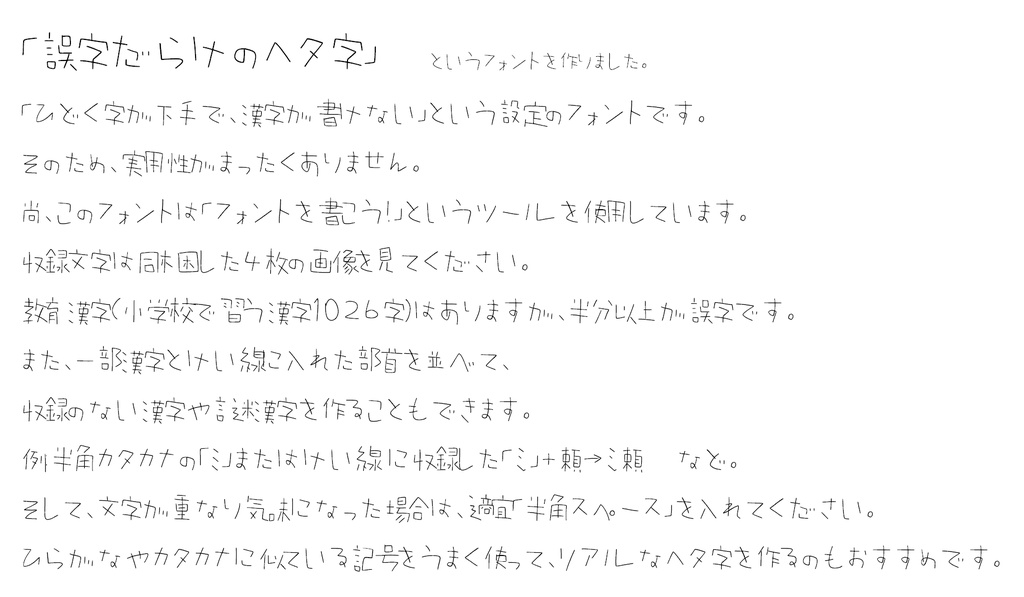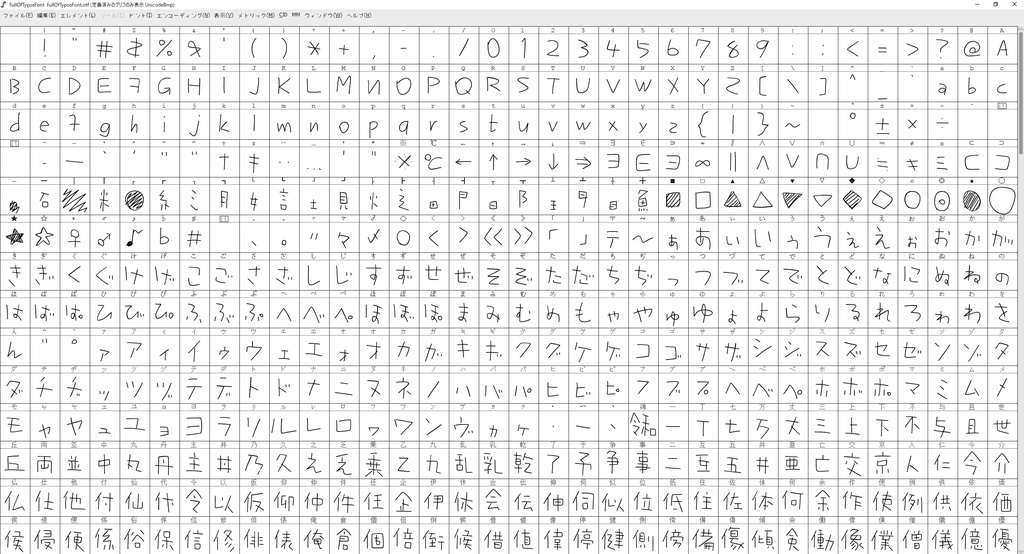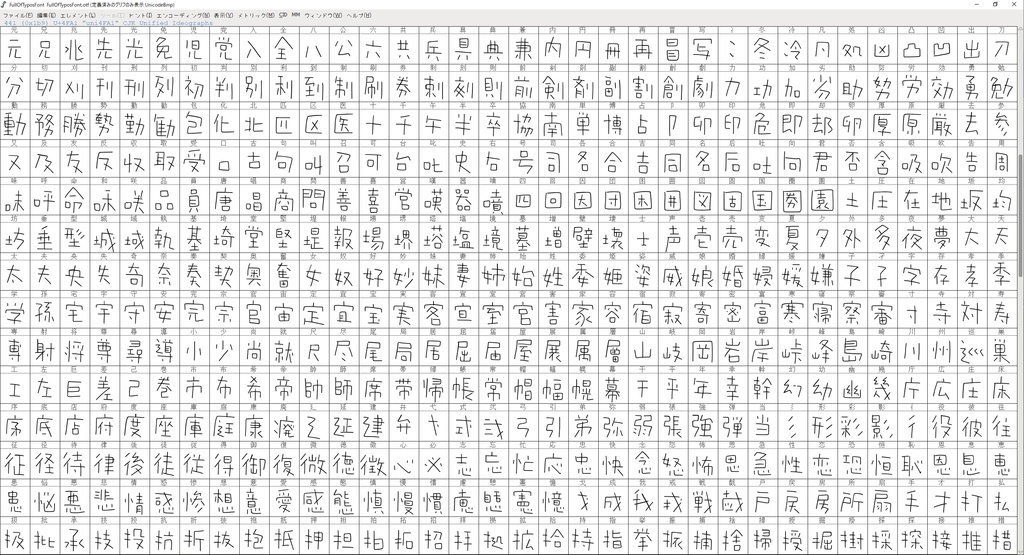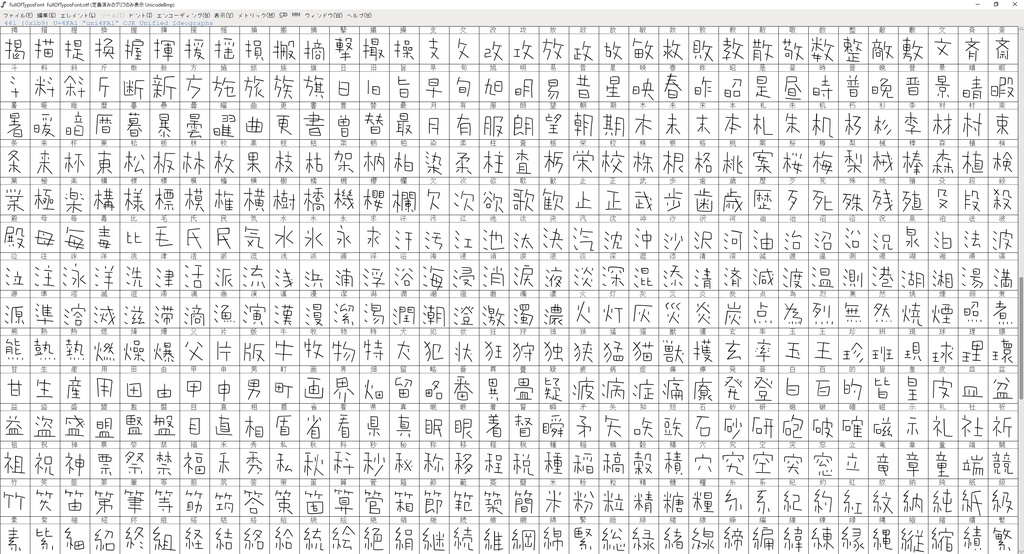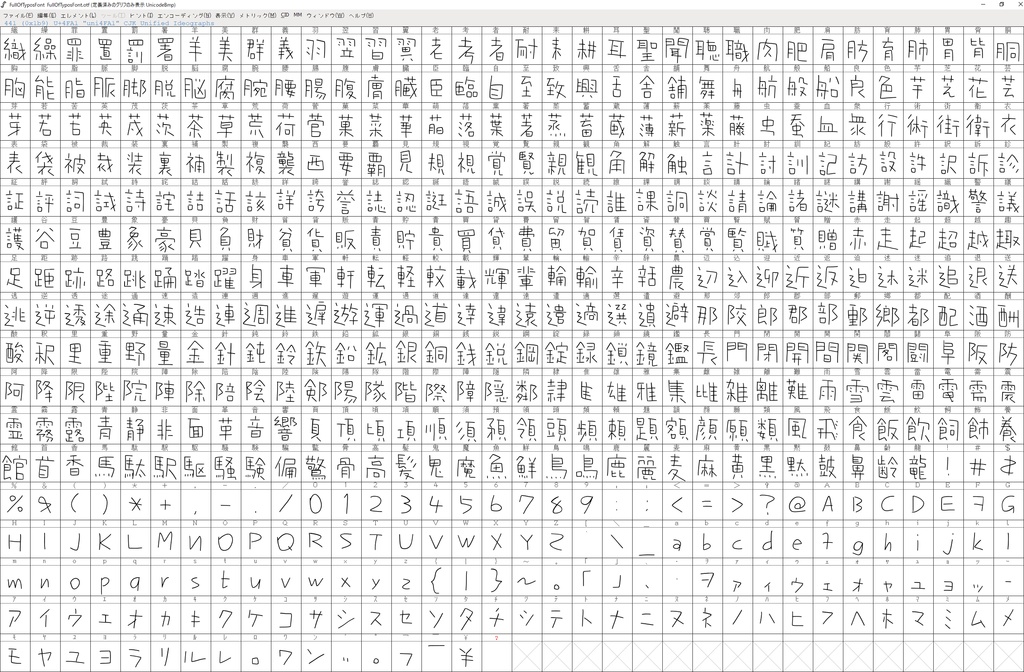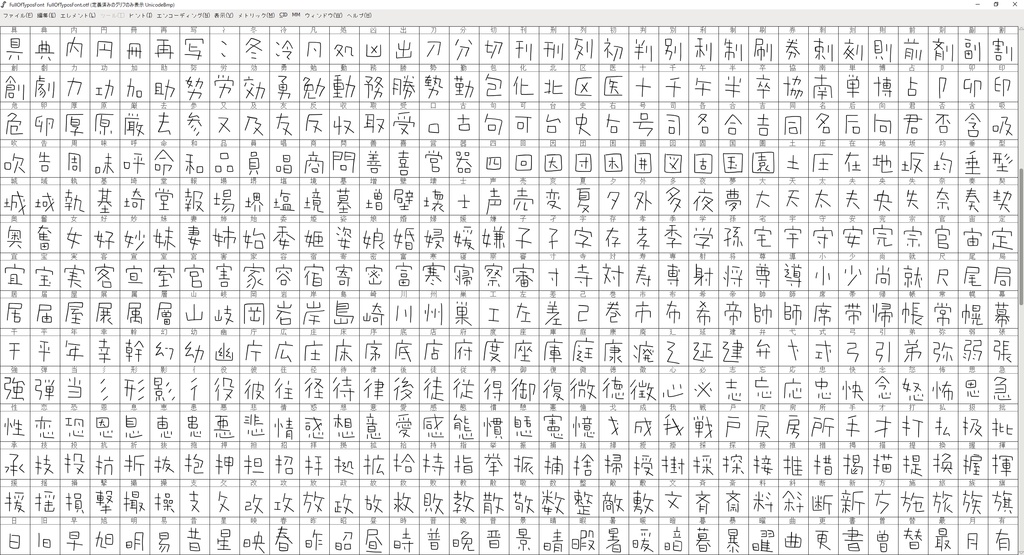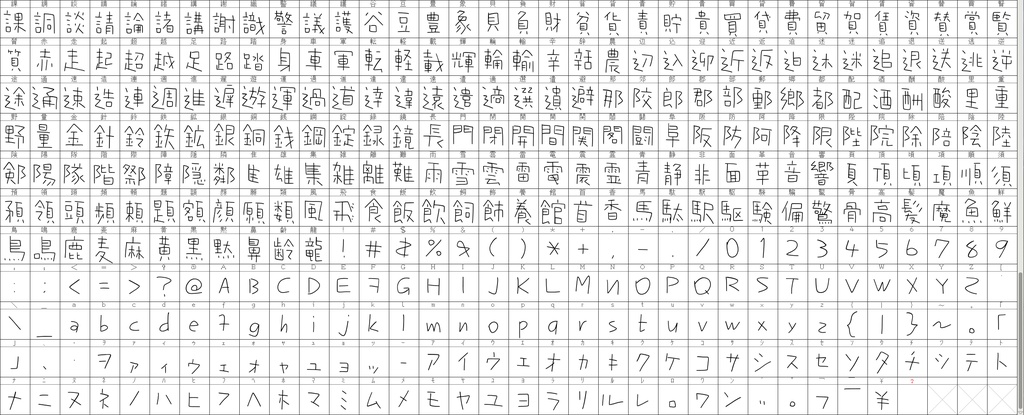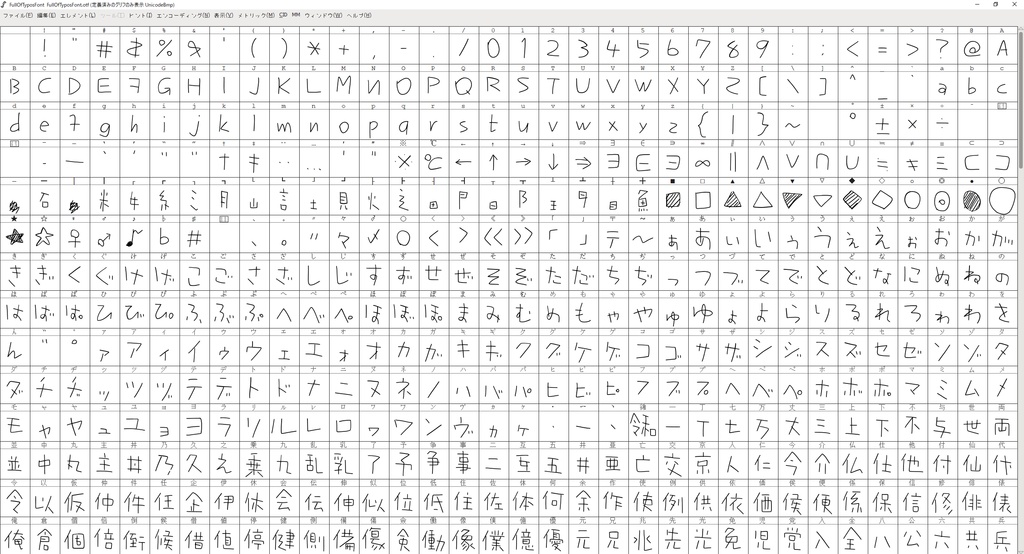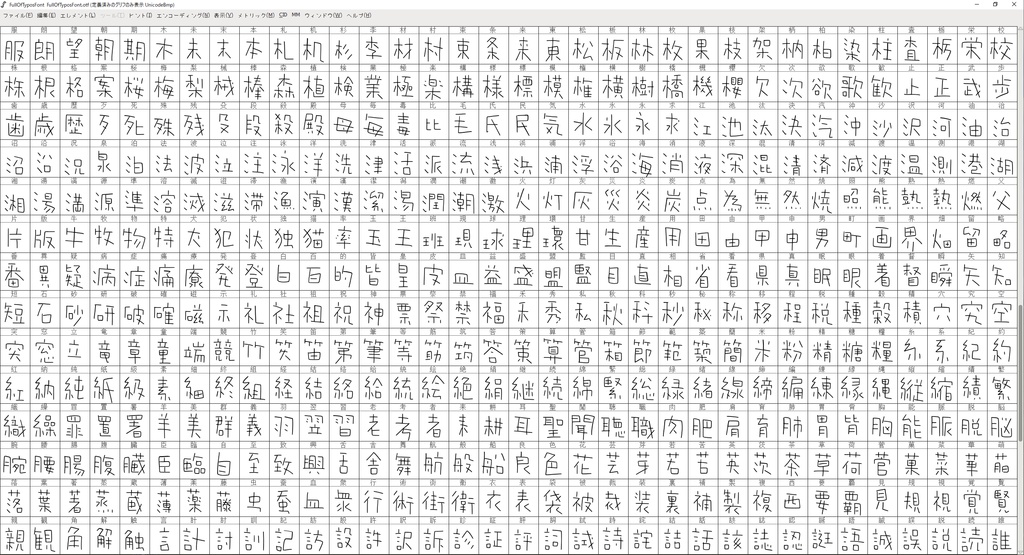
誤字だらけのヘタ字(フリーフォント)
「誤字だらけのヘタ字」というフォントを作りました。 「ひどく字が下手で、漢字が書けない」という設定のフォントです。 そのため、実用性がまったくないジョークフォントです。 尚、このフォントは「フォントを書こう!」というツールを使用しています。 https://buttaiwan.github.io/writemyfont/ja.html 収録文字は同梱した4枚の画像を見てください。 商用利用可能(自己責任)、反社会的利用禁止でお願いします。 教育漢字(小学校で習う漢字1026字)はありますが、半分以上が誤字です。 一部英字や記号にも誤字が混ざっています。 また、罫線や一部漢字には、謎漢字を作るための部首や、一旦書いてからギザギザの線でごまかした「口偏」もあります。 例:半角カタカナの「ミ」またはけい線に収録した「┐」+頼→瀬 など。 そして、文字が重なり気味になった場合は、適宜「半角スペース」を入れてください。 ひらがなやカタカナに似ている記号や漢字をうまく使って、リアルなヘタ字を作るのもおすすめです。